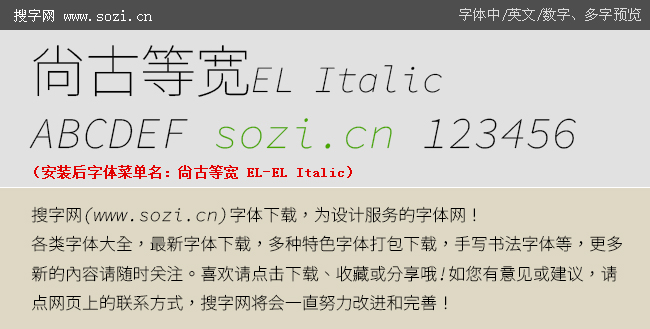
尚谷等宽ExtraLightIt(EL-Italic)
搜字网提供一款尚谷等宽ExtraLightIt(EL-Italic)中文字体下载,尚古字体是一套泛中日韩传承字形(旧字形),基于思源黑体、思源宋体、思源等宽以及思源系列衍生字型制作,包含黑体、明体、圆体、等宽以及简转繁字型。这款字体无论是个人还是企业都可以自由免费商用,无需知会或者标明原作者。适合包装设计、海报设计、广告设计等应用。